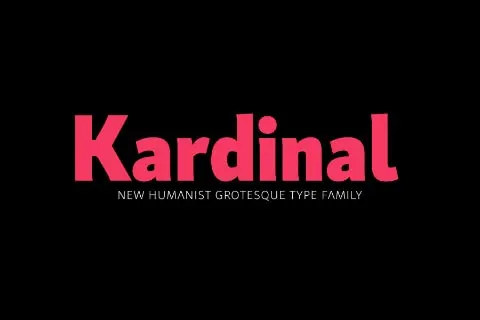
Na introdução ao mundo das fuentes digitais, apresentamos Kardinal Font Family, uma família tipográfica de linhas retas criada pelo designer Hamilton para Befonts. Este é um tipo humanístico sans serif, com 32 pesos diferentes que vão desde o Espinca (thin) até a Negrito (black). O famoso projeto Lettersoup também fez deste conjunto único uma experiência visual emocionante. A característica mais notável de Kardinal é seu uso extrafeito para itálico e versões em minúsculas grandes, oferecendo um toque especial ao texto. Essa família é perfeitamente adequada para textos pequenos, livros, magazines, identidade visual, cartazes, design web e aplicações de tela. Eles se destacam não apenas por sua grande variedade de pesos e estilos únicos, mas também pela excelente legibilidade e aprimoramento da leitura em todos os formatos de mídia. Tornar o seu projeto mais atraente nunca foi tão fácil com Kardinal Font Family, uma fonte que vai muito além das suas aparentes características. Seja você um designer gráfico ou editor de texto, Kardinal oferece tudo o que precisa para tornar seus projetos singulares e impecáveis.